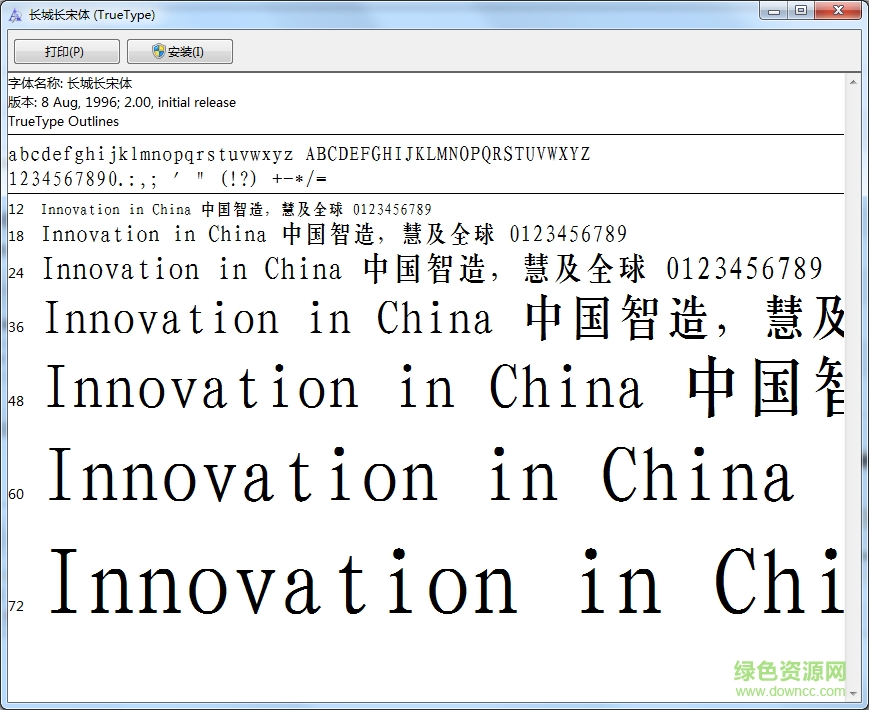
長(zhǎng)城長(zhǎng)宋體是一款非常工整的長(zhǎng)城字體,由于結(jié)合了宋體的元素,字體看起來非常的清新自然,字體整體偏細(xì)長(zhǎng),支持中文、英文和阿拉伯?dāng)?shù)字,歡迎有需要的朋友到綠色資源網(wǎng)下載使用!
長(zhǎng)城長(zhǎng)宋體筆畫有粗細(xì)變化,而且一般是橫細(xì)豎粗,末端有裝飾部分(即“字腳”或“襯線”),點(diǎn)、撇、捺、鉤等筆畫有尖端。